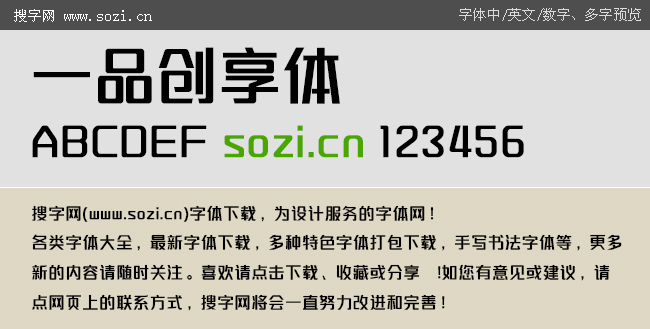
一品創(chuàng)享體
搜字網(wǎng)給大家提供一款一品創(chuàng)享體中文字體下載,一品創(chuàng)享體是一款由吉頁字庫創(chuàng)始人孫新恒受一品威客邀請(qǐng)作為主創(chuàng)設(shè)計(jì)師,聯(lián)合打造的一款公益造字百人計(jì)劃的字體。字體筆畫連接處采用倒角設(shè)計(jì),使字體更加生動(dòng),線條圓潤風(fēng)趣,又簡潔明快。適用于海報(bào)設(shè)計(jì)、包裝設(shè)計(jì)、廣告設(shè)計(jì)等場景。